楷书是学 书法的基本功,学书宜从楷书入手。古人曾有这样一个比方:“楷如立,行如行,草如走。”意思是正如人总要先学会站立,然后才能学会走路或奔跑,有了楷书作基础才能写好 行书和草书。因为楷书端正,一笔是一笔,行笔速度也较缓慢,这就容易使初学的人学得像,写得准确。
学楷书,从点画开始。掌握了点画的基本形态和写法,则不管字帖中的字体的笔画如何变化,万变不离其宗,临摹起来都容易抓住要领,学到它的形和神了。
一、点
点的基本形式:头尖、尾圆、腹平、背圆。写法如图:
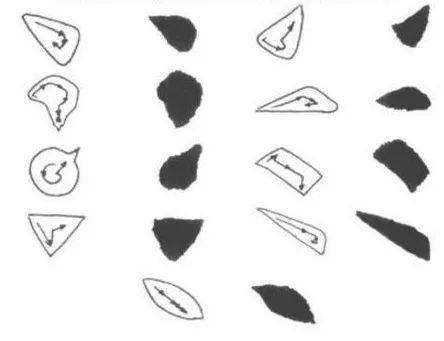
1.锋尖落纸(可先将笔舔尖,轻轻落笔)。
2.向右下将笔毫向两边铺开,笔渐下渐重。
3.到下半部,将笔锋稍提起,再放下向背部兜围扭动一下。
4.轻快有力地从下腹出锋。
点的写法要求:顾盼生姿、向背分明。
点的种类:
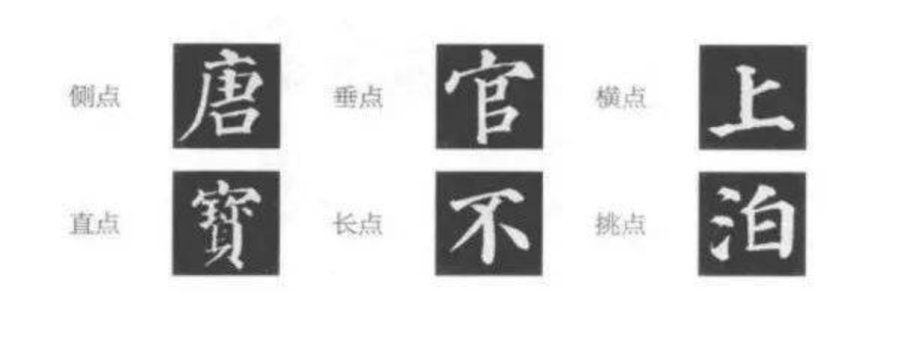
二、横
基本形式:头方(斜)尾圆,中段略细。
横的写法如图:
1.笔锋先从右向左逆行。
2.直(或稍斜)落笔。
3.通过提按使笔锋回复中锋,沿着笔画中线向右运行,中段稍提笔。
4.至结尾处笔锋稍提起,再向右下放下,像写点那样,兜围扭动一下,然后迅速有力地向左收锋。
注意:不能使劲顿笔,中段与两头也不能一样粗细,显得僵直。
横的种类有
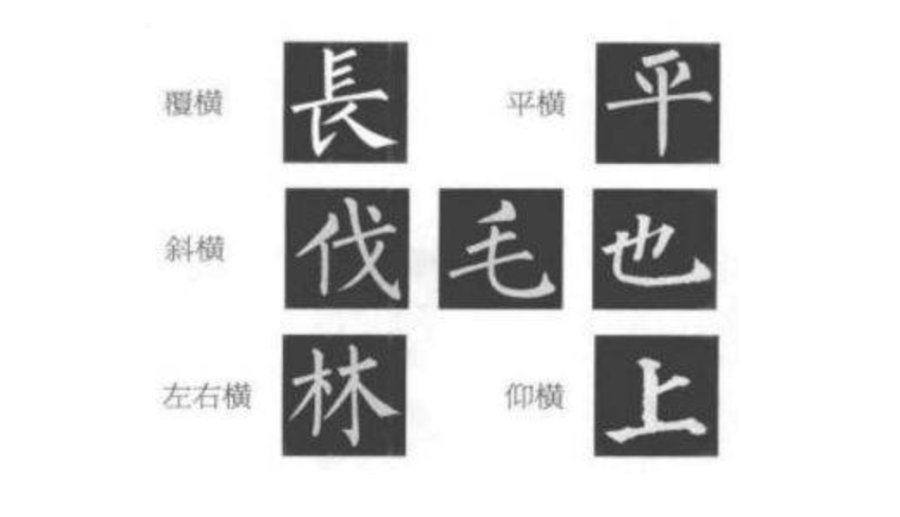
三、竖
竖,起支柱作用,要求写得劲挺有力,像人胸腰挺起。基本形式有垂露竖和悬针竖两种。
垂露竖写法如图:
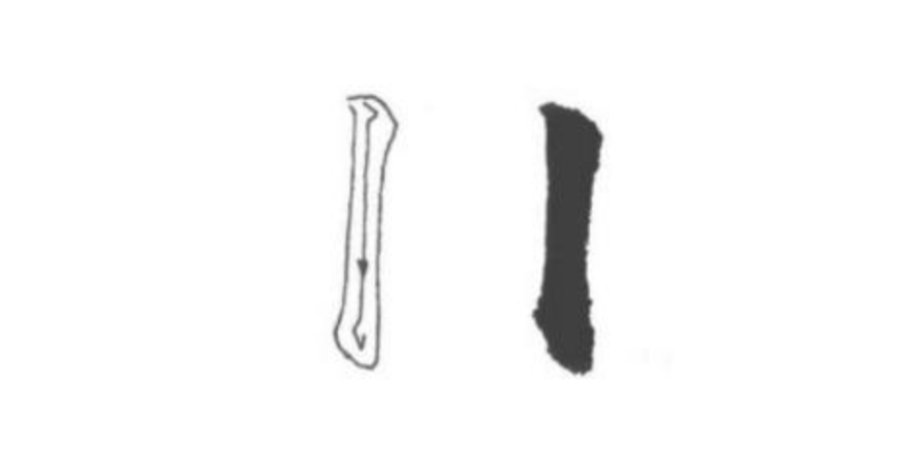
1.笔锋向上逆行。
2.横(或稍斜)落笔,笔向右斜。
3.笔锋轻轻向左右扭动一下,调整笔锋然后向下行笔。
4.至尾部,略提锋,从左向上收锋。
悬针竖:写法与垂露竖的不同之处仅在于它在尾末要出锋。要点:像一枚针,写得粗壮,出锋不宜太长太细。
如图:
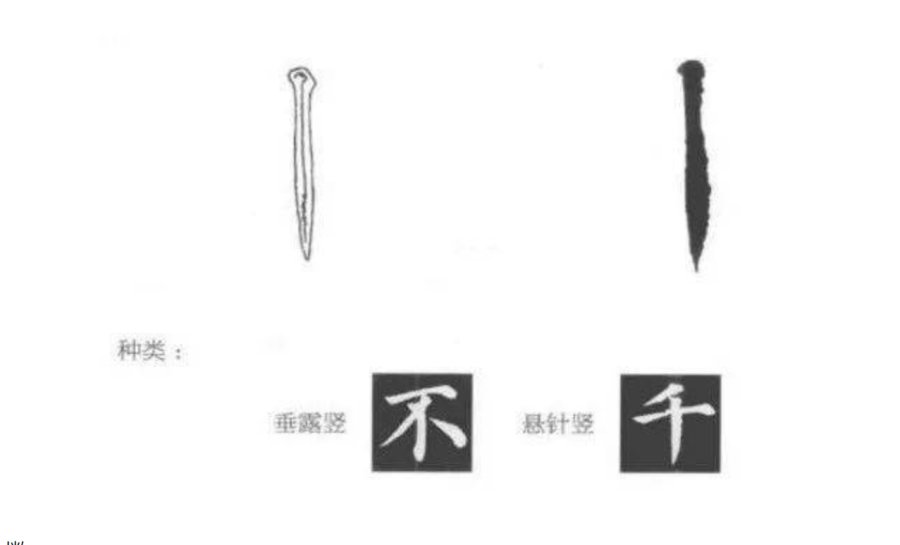
四、撇
汉字的笔画大多是向右向下的,右手写这些笔画都较顺手,唯独撇是向左伸展的,写起来较别扭。这是写字的重点。
基本形式:尾部略肥和上扬,姿态舒展。写法如图:
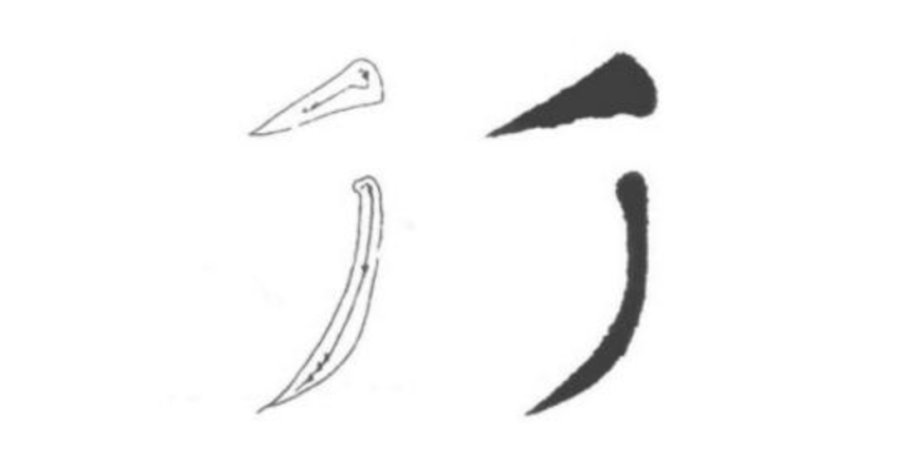
1.向上逆锋而起。
2.斜落笔。
3.调整笔锋,让中锋缓缓行笔。
4.至尾部,快而有力地出锋,使力送到撇尖。
注意:忌“中途拔出”和“头重尾飘”,以女同志梳头的速度和力度书写撇较适宜。
短撇的写法:如“斤”“生”落笔后 ,稍作扭动,调整笔锋,快速撇出。
撇的种类:
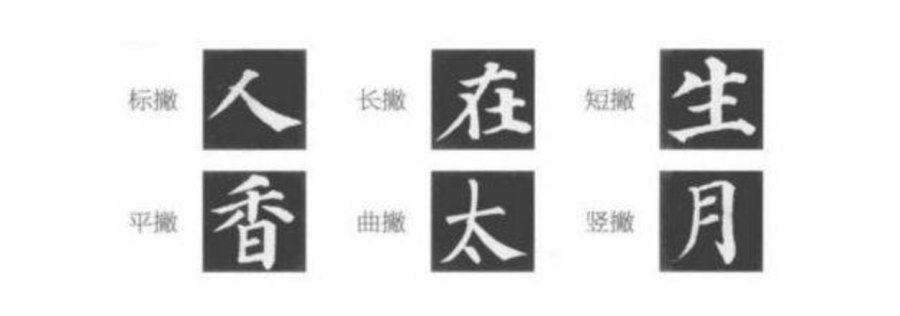
五、捺
基本形式:一波三折的姿态。
一折:从头到颈部。
二折:颈到捺脚。
三折:捺脚到锋尖。
一波:整笔有起有伏。像波浪。
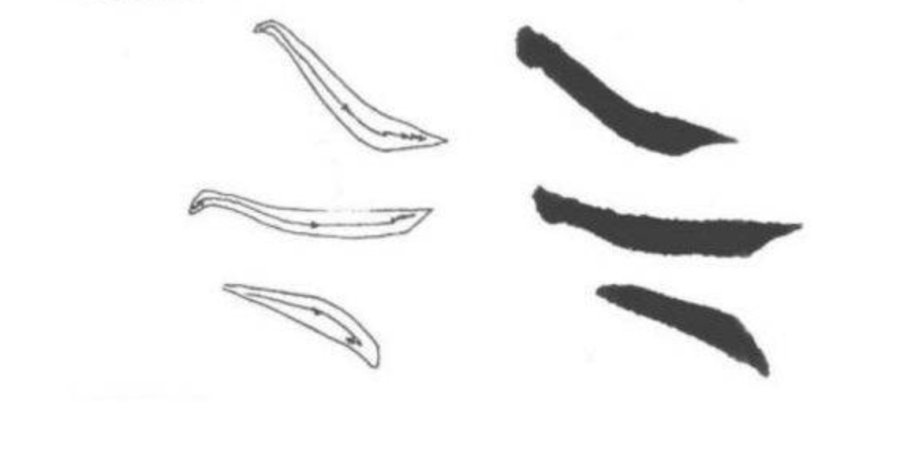
1.逆锋而起。
2.轻轻向下落笔。
3.略向左上起笔,至颈部,锋稍提使颈部略细。
4.向右下渐渐将笔毫铺开,至捺脚处。
5.轻向左推,调整笔锋,沉着痛快地扬出锋。
注意:
1.捺画出线要直。
2.捺脚要有力。
3.笔不能向下拖。
捺和撇往往同时存在,连在一起练习为好,如“大”“来”。
捺的种类:
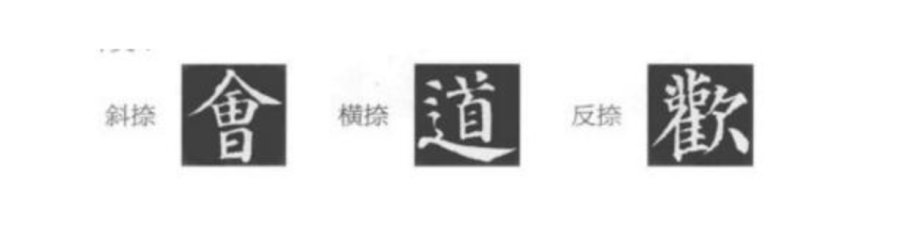
六、钩
钩是其他笔画的附着物。
“竖左钩”做到平、锐、满。即竖要平,锋要锐,钩要饱满。
写法:写好一竖将要钩出时,先将笔锋往上提,使笔毫收聚,放下,然后用力向左平推出来。如图:
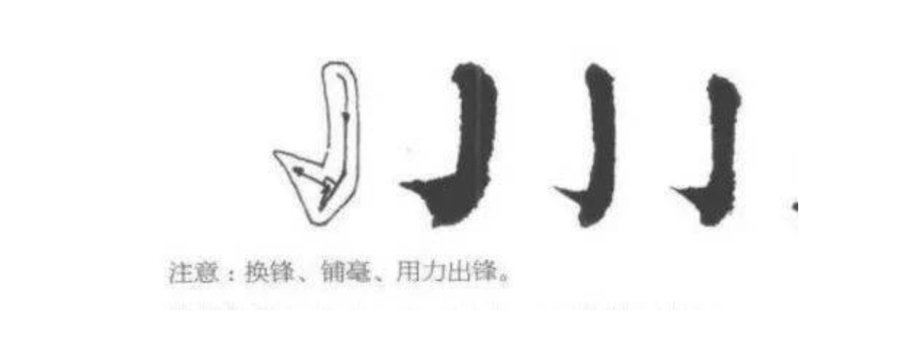
钩的种类:
七、挑
基本形式:像反向的短撇。写法如图:
1.逆锋而起。
2.斜落笔。
3.稍作扭动,调整笔锋。
4.快而有力地向右上方挑出,送到笔画的尖端。
八、折
折由一个横画和竖画组合而成。如图:
以上为八个基本笔画。初学书法者对这八个笔画应练透。有人可能会认为这样一笔一画写字,写字的进度会慢,其实,恰好相反,学会了这八种基本笔画,就会触类旁通,举一反三,较陕地掌握楷书笔画的书写规律。